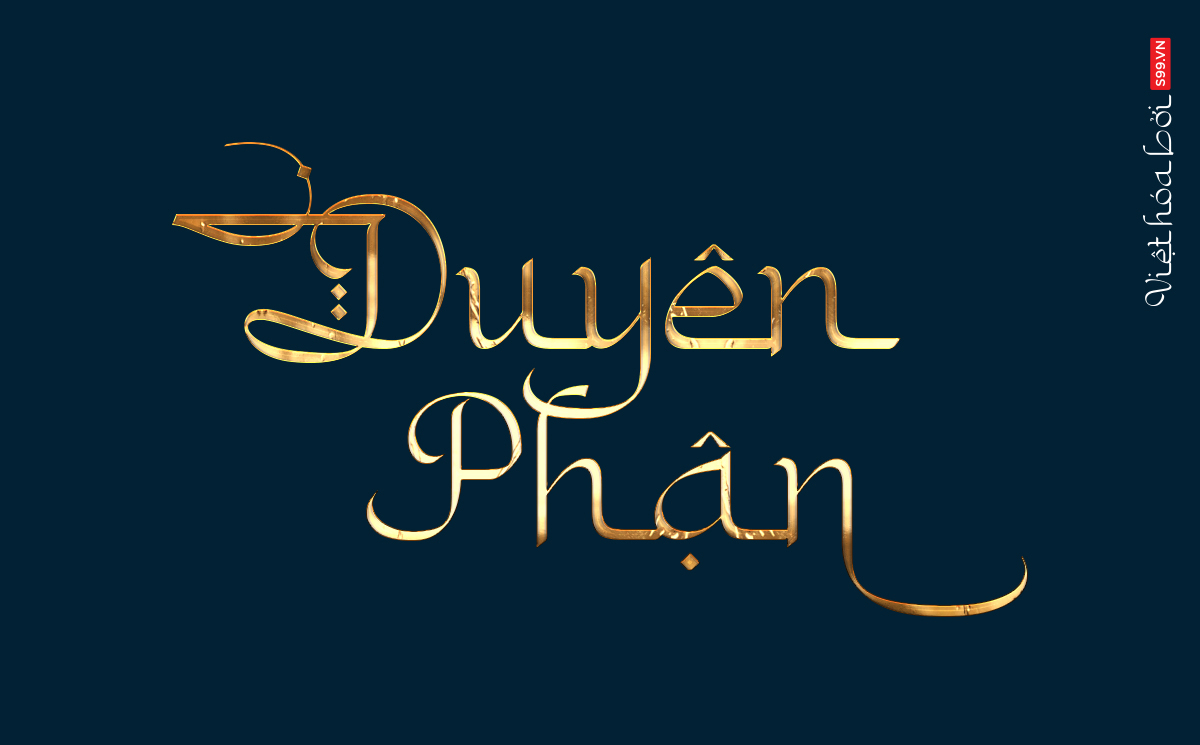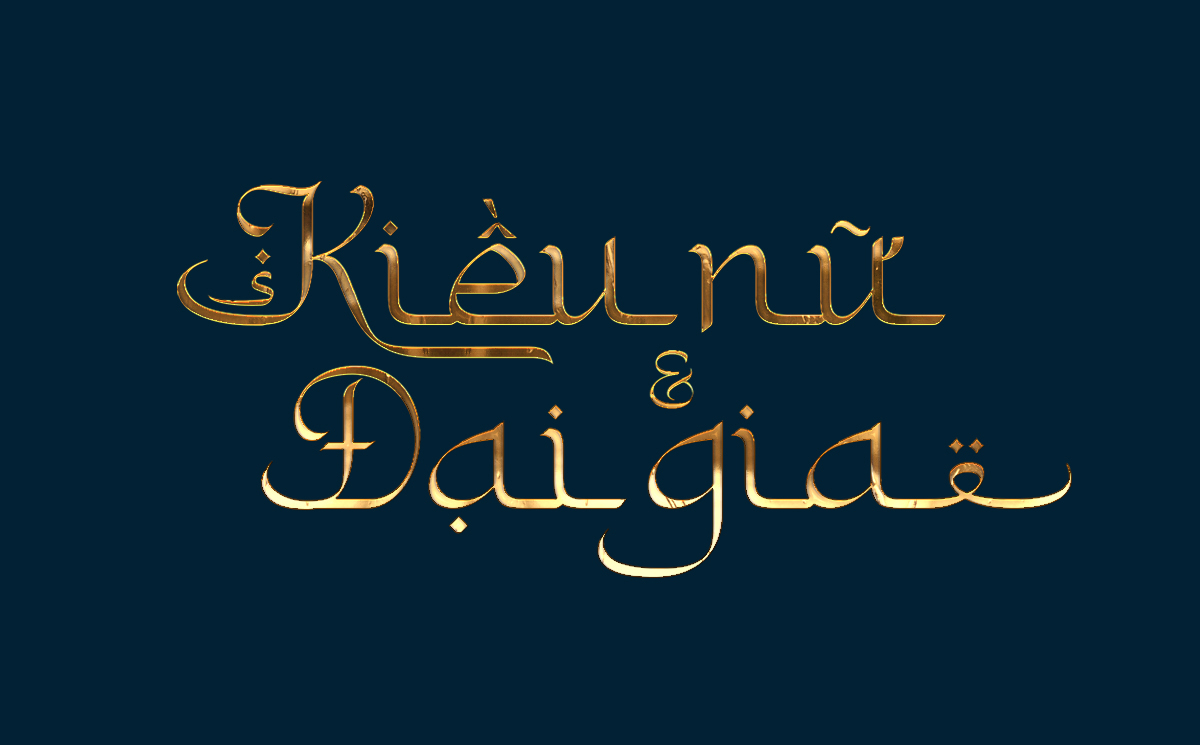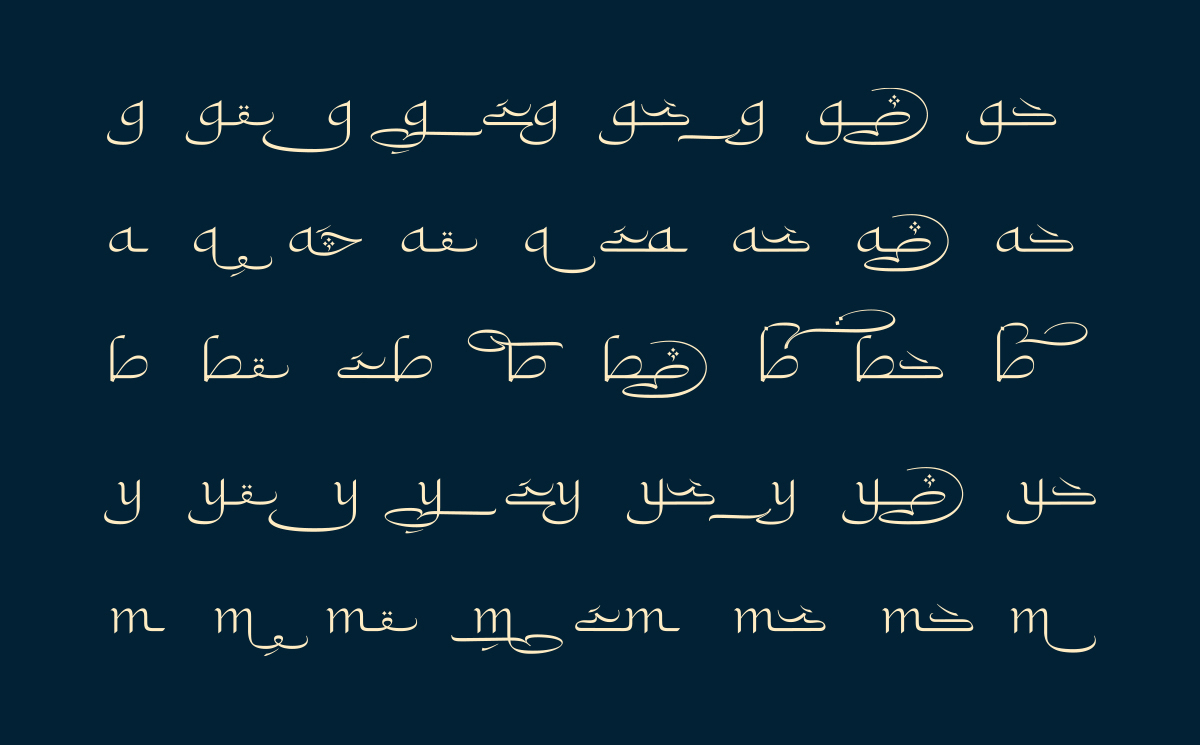
Tác giả Kabyah
Hôm nay mình muốn chia sẻ với bạn một bộ font mà mình rất ưng ý sau khi hoàn tất quá trình Việt hóa: TH Kabyah – một kiểu chữ mang đậm phong cách cổ trang, nhưng lại rất dễ đọc, dễ ứng dụng và hỗ trợ tiếng Việt đầy đủ.
Font này ban đầu có tên gốc là Kabyah, được thiết kế bởi một tác giả đến từ Indonesia – Fadiel Muhammad. Tuy nhiên, khi mình thấy font này, mình ngay lập tức nghĩ tới những thiết kế kiểu poster phim kiếm hiệp, tiêu đề truyện dân gian, hay cả menu nhà hàng kiểu xưa. Đó là lý do mình quyết định Việt hóa nó và đặt tên lại là TH Kabyah (TH tức là phiên bản đã hỗ trợ tiếng Việt).
Kiểu dáng font như thế nào? Có gì đặc biệt?
Font TH Kabyah có nét chữ thanh mảnh, đầu nét hơi nhọn, cong nhẹ. Cảm giác khi nhìn vào giống như chữ viết tay thời xưa, nhưng không quá bay bướm như thư pháp. Nó giữ được sự nghiêm túc, trang trọng, mà vẫn thân thiện và nhẹ nhàng.
Mình đã cân chỉnh lại các dấu, ký tự tiếng Việt để nó không bị chen lấn, vỡ chữ hay lệch vị trí – một lỗi thường thấy khi ta dùng font ngoại chưa Việt hóa.
Font đã hỗ trợ tiếng Việt chưa? Có bị lỗi không?
Tất cả các ký tự như ă, â, ê, ô, ư, đ, các dấu thanh sắc, huyền, hỏi, ngã, nặng đều được kiểm tra kỹ. Font dùng được mượt mà trên: PowerPoint, Canva, Photoshop, Illustrator, các trình duyệt web, In ấn không lỗi nét, không vỡ dấu
Font có glyph thay thế đa dạng
Một điểm nổi bật khiến TH Kabyah khác biệt và đáng giá hơn nhiều font cổ trang khác, chính là bộ glyph thay thế (alternates) cực kỳ phong phú – như bạn có thể thấy trong hình minh họa.
Đặc điểm nổi bật của các glyph thay thế:
• Biến thể đầu – giữa – cuối của chữ cái được thiết kế tỉ mỉ, giúp font linh hoạt hơn khi trình bày dạng chữ tay, dòng thơ, hoặc tiêu đề.
• Một số chữ có thêm chi tiết trang trí như “hạt kim cương”, “nét móc cách điệu” làm tăng tính thẩm mỹ, giống như một phiên bản chữ viết tay kết hợp typography hiện đại.
• Đường nét mảnh – uốn lượn mềm giúp tạo cảm giác sang trọng, bay bổng, mà vẫn giữ chất cổ trang thuần túy.
Tóm lại: Có nên thử TH Kabyah?
Nếu bạn đang tìm một font mang hơi hướng cổ trang, thanh mảnh, dễ dùng và đã Việt hóa hoàn chỉnh, thì TH Kabyah là lựa chọn rất đáng thử. Font hiển thị tốt trên mọi nền tảng, không lỗi dấu, hỗ trợ thiết kế cả in ấn lẫn số hóa. Đặc biệt, bộ glyph thay thế đa dạng giúp bạn linh hoạt sáng tạo trong tiêu đề, logo, hay poster. TH Kabyah vừa đủ truyền thống để tạo cảm xúc, vừa đủ hiện đại để ứng dụng dễ dàng.